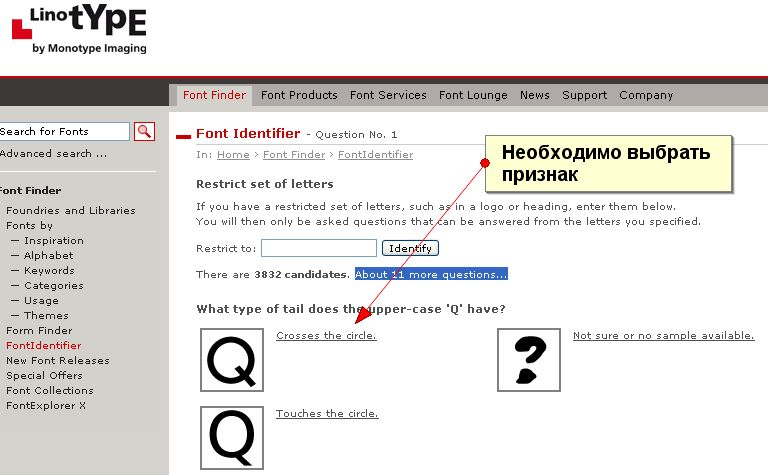
Как определить строку с картинки
Бывают случаи, когда вы где-то находите случайное изображение с отличным текстом, но не уверены, какой шрифт использовался на изображении. Выделение линий на изображении — полезный прием, который вам следует знать. Вы можете найти шрифт, который использовался на изображении, и скачать его. Есть много подобных вариантов использования для выбора шрифта из изображения. Если вы также ищете способ распознать шрифт на фотографии, у нас есть идеальное руководство для вас. Итак, продолжайте читать эту статью о том, как выбрать шрифт из изображения.
Способ 1. Используйте сторонние инструменты для определения шрифта на изображении.
В этом случае вы можете использовать онлайн-инструменты для идентификации шрифта на изображениях. Но иногда вы можете быть недовольны результатами, которые дают вам эти инструменты. Помните, что вероятность успешного распознавания шрифта зависит от ряда элементов, например:
- Качество изображения: Если вы загружаете растровые изображения, автоматические средства поиска шрифтов сопоставят шрифт на изображении со своей базой данных шрифтов.
Кроме того, это подводит нас к следующему фактору. - База данных шрифтов: Чем больше база данных шрифтов, тем больше шансов, что автоматические шрифты точно их идентифицируют. Если первый инструмент, который вы использовали, не дал удовлетворительных результатов, попробуйте альтернативный инструмент.
- Направление текста: Если текст выгравирован, слова перекрываются и т. д., распознаватель шрифтов не распознает шрифт.
Вот несколько надежных распознавателей шрифтов, которые помогут вам определить шрифт на изображении:
1. Идентификационный шрифт: в отличие от других онлайн-распознавателей шрифтов, Идентификационный шрифт Нужно больше ручной работы.
Следовательно, для получения строки требуется много времени, но, с другой стороны, это не вызывает ошибки в алгоритме. Вы можете искать базовые шрифты в нескольких категориях на главной странице или щелкнув параметр «Шрифты по внешнему виду». Появятся различные вопросы относительно шрифта, который вы ищете, и вы можете отфильтровать нужный шрифт среди них. Загрузка изображения прямо на веб-сайт занимает действительно много времени, но этот инструмент также дает относительно хорошие результаты.
2. Сопоставитель шрифтов белка: Это отличный инструмент для распознавания шрифтов на изображениях, где вы можете скачать сотни нужных вам шрифтов, пообщаться с другими любителями шрифтов в Интернете и купить футболки! это содержит Отличный инструмент для определения шрифтов С его помощью вы можете перетаскивать изображение, а затем сканировать его на наличие линий. Это очень надежный, точный и предлагает вам несколько шрифтов с лучшим соответствием!
3. ЧтоШрифт: WhatFontIs Это отличный инструмент для определения шрифта на изображении, но вы должны зарегистрироваться на их веб-сайте, чтобы пользоваться всеми их предложениями.
Загрузите изображение, содержащее шрифт, который вы хотите выбрать, затем нажмите «Продолжить». Как только вы нажмете на
4. Сопоставитель шрифтов: Считается Матчератор Fontspring Более гибкий в использовании, чем первый вариант, поскольку единственным требованием является щелчок по шрифту, который вы хотите выбрать. Он имеет своеобразный дизайн и, таким образом, предлагает привлекательные представления имен шрифтов, которые он отображает. Но, с другой стороны, если вам нужно скачать нужный шрифт, это может дорого обойтись. Например, если вы хотите купить семейство из 65 шрифтов, таких как курсив Minion Pro, средний, полужирный и т. д., это будет стоить 569 долларов! Но не волнуйтесь.
5. WhatTheFont: это программное обеспечение является самым популярным инструментом для распознавания шрифтов на изображениях в Интернете. Но есть некоторые правила, которых следует придерживаться:
- Убедитесь, что линии на изображении остаются отдельными.
- Высота символов на изображении должна быть 100 пикселей.
- Текст на изображении должен быть горизонтальным.
Как только вы загрузите свое изображение и наберете его буквами, результаты будут отображаться на следующей странице. Результаты отображаются с названием шрифта, примером и именем создателя. Если вы все еще не можете найти нужный вам матч, приложение предлагает проконсультироваться с командой экспертов.
6. Quora: Quora Это отличное приложение, куда пользователи заходят и ищут ответы на свои вопросы. Во многих темах на Quora есть категория, называемая идентификацией лица.
Вот шаги, как выбрать шрифт из изображения с помощью инструмента WhatFontIs.
1. Загрузите изображение, содержащее нужный вам шрифт.
Примечание. Рекомендуется загружать изображение с высоким разрешением, которое не разрывается даже при увеличении. Если вы не можете загрузить изображение на свое устройство, вы можете указать URL-адрес изображения.
2. Обычно мне нравится иметь набор шрифтов из 3 разных гарнитур, который часто включает:
Serif — те классические шрифты, которые имеют то, что мы называем «ножками», например Bodoni, Times и Playfair.